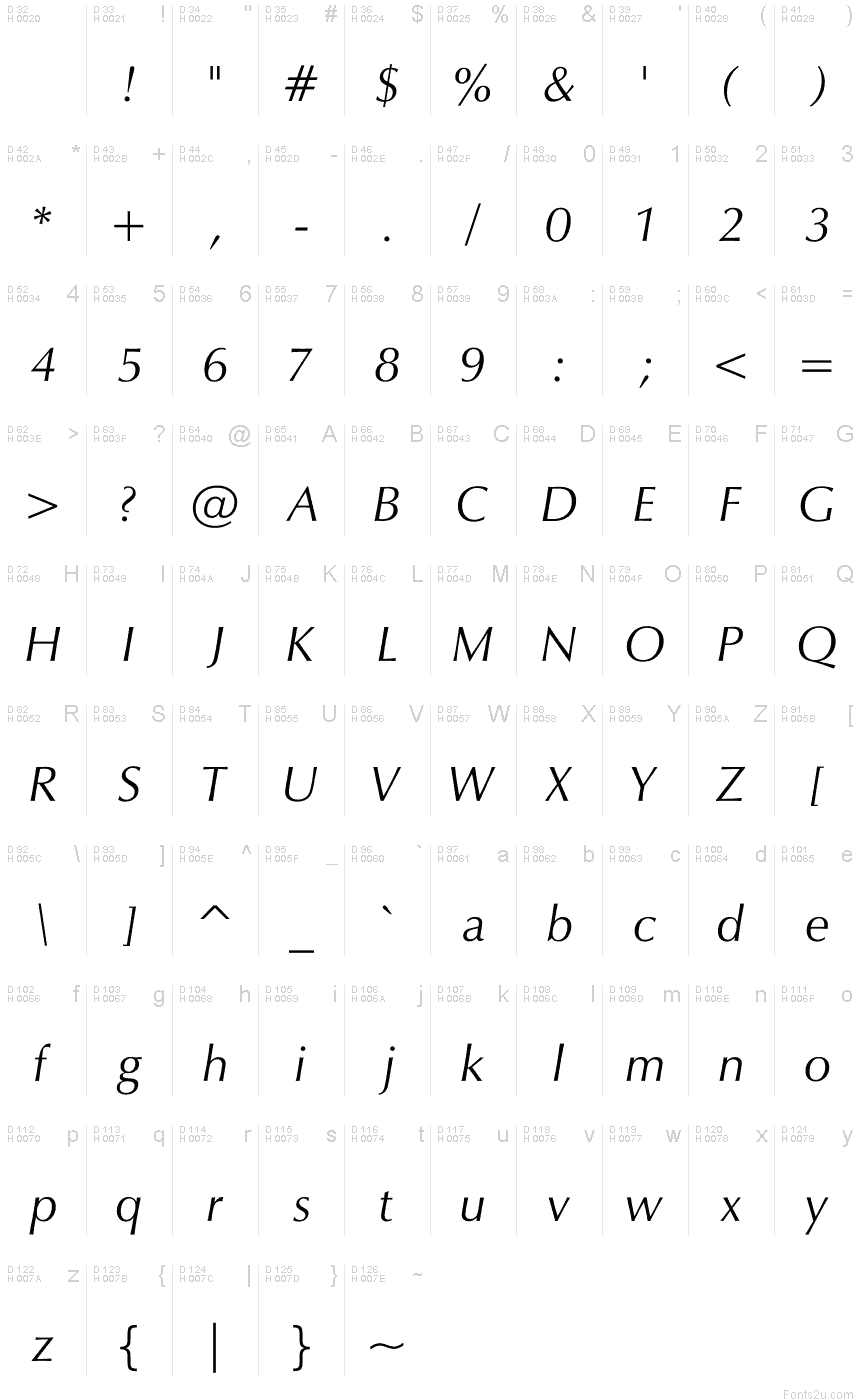
Zap Italic è un carattere sans-serif corsivo gratuito con lettere finemente disegnate, tratti lunghi e terminali angolari troncati. La sua forte inclinazione salta subito all'occhio.
Le testate di moda e il packaging cosmetico possono sfruttare il suo movimento elegante, ma la stessa sagoma nitida si adatta anche a manifesti musicali e grafica per eventi. Le lettere risultano raffinate anziché rigide. In questi contesti, la pronunciata inclinazione trasforma le parole in elementi grafici direzionali, collegando un branding curato a un lavoro culturale più espressivo.
Zap Italic